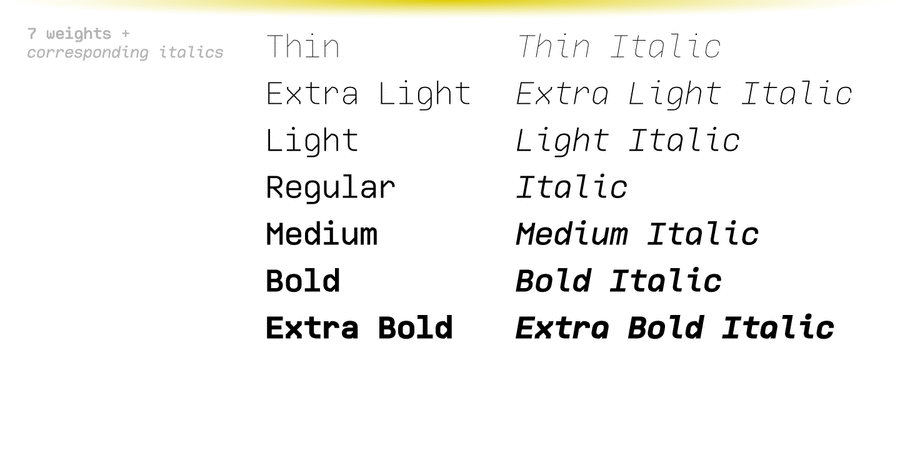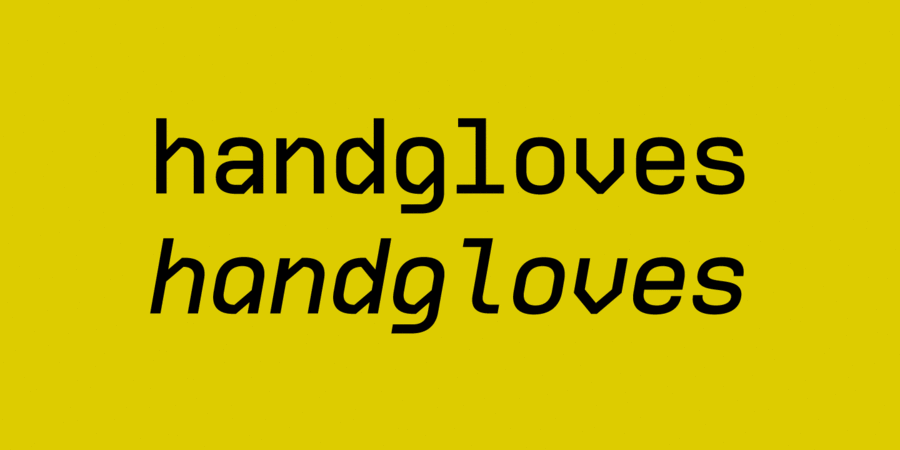
Моноширинна екранна гарнітура, натхненна старими відеомагнітофонами та камерами, шрифтами їх екранних інтерфейсів. Цей шрифт відрізняється своїми діагоналями, кути яких обмежені 45°, що дає специфічну текстуру та ідеальну читабельність у дрібних розмірах. Гарнітура має 7 накреслень різної насиченості з відповідними курсивними версіями. Кожне анкреслення містить понад 500 ґліфів для підтримки безлічі мов, включно з кирилицею. Шрифт розробив Андрій Константинов в студії Mint Type у 2020 році.